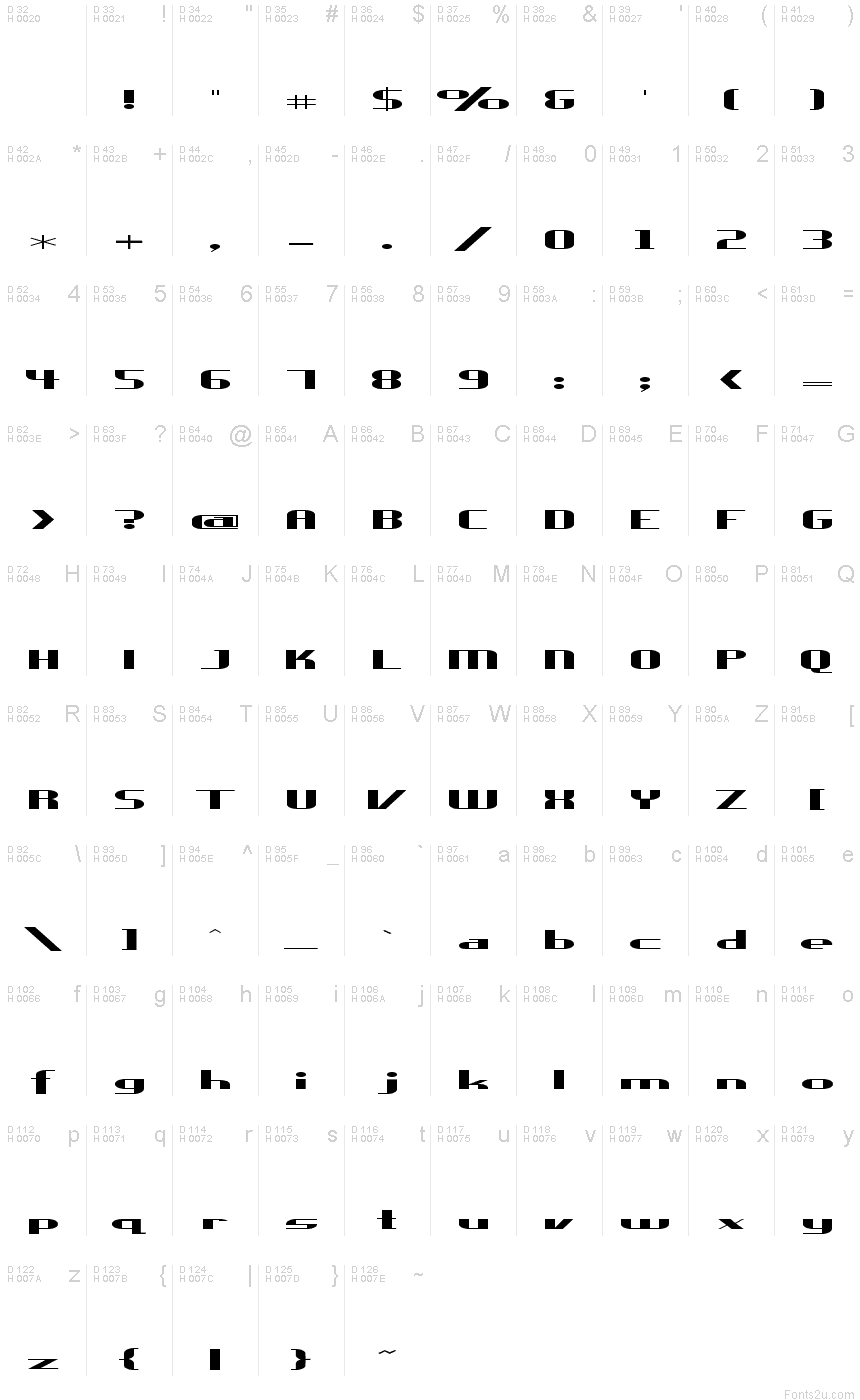
Ureka, bezplatné techno písmo od Kairee z roku 1999, má elegantní digitální vzhled postavený na širokých vodorovných blocích, čtvercových řezech a ostrých rozích. Písmena působí protaženě a nízce, s dlouhými příčkami a useknutými otvory, díky čemuž celý font působí jako aerodynamický nápis spíše než jako běžné titulkové písmo.
Přirozeně zapadne do sci-fi plakátů, herních log, klubových letáků, titulků a obalů alb, kde bezplatný font potřebuje kompaktní, futuristický hlas. Použijte ho pro krátké nadpisy, branding, štítky ve stylu rozhraní nebo texty na obálkách, zejména pokud chcete, aby písmena do sebe zapadla a vytvořila jeden rychlý, technicky zpracovaný tvar.